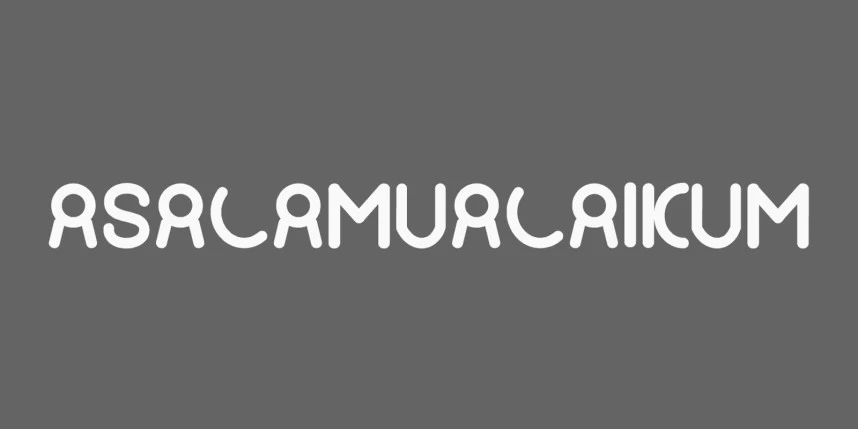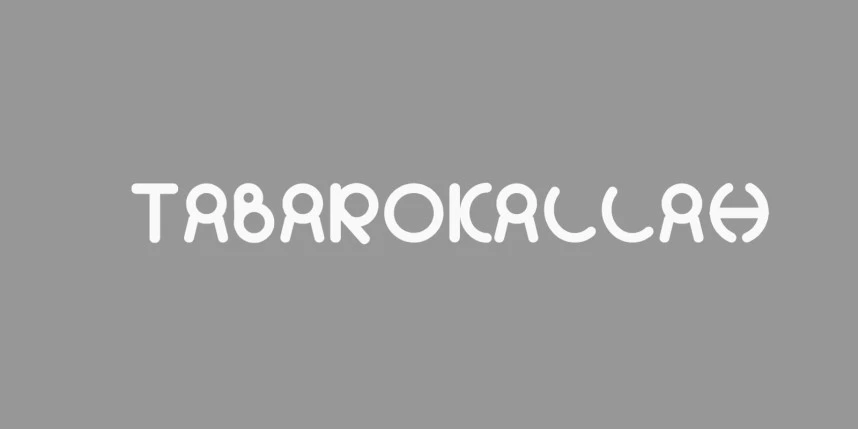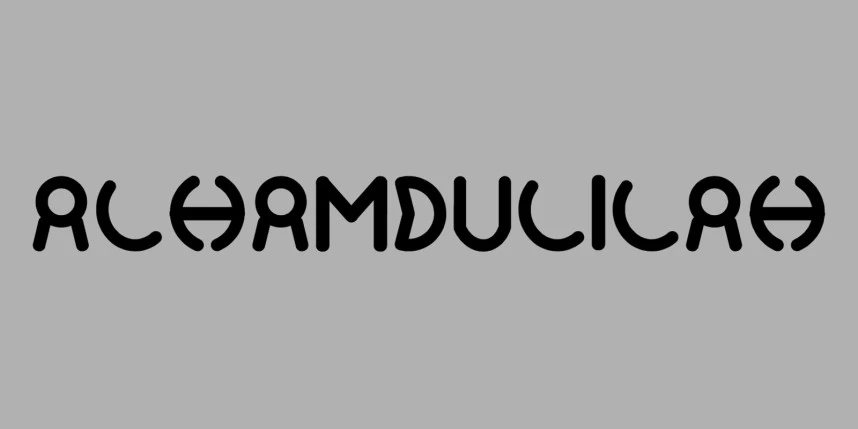
Elhamdülillah Başlık Yazı Tipi
Alhamdulilah Display Font, Arapça yazı stilinin güzelliğinden ve İslami hat sanatının zarafetinden ilham alan bir fonttur. Yumuşak hatlar ve zarif eğrilerle tasarlanmış bu font, her karaktere manevi ve rafine bir dokunuş katar.
Alhamdulilah Display Font, Arap yazısının güzelliğinden ve İslami hat sanatının zarafetinden ilham alan bir yazı tipidir. Yumuşak çizgiler ve zarif eğrilerle tasarlanmıştır; bu yazı tipi her karaktere ruhani ve zarif bir dokunuş getirir.